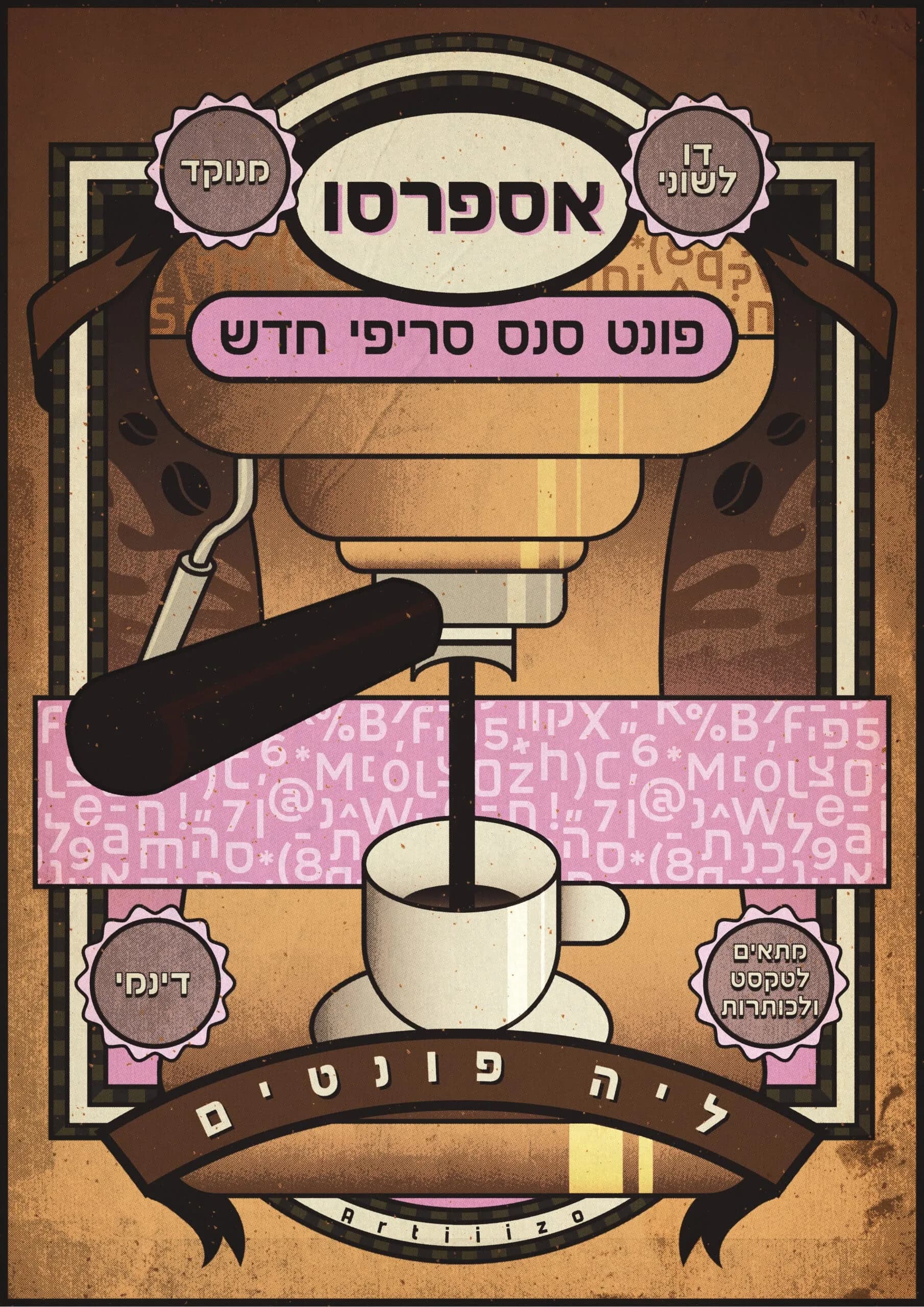
אספרסו אספרסו הוא פונט שיעיר את העיצובים שלכם! - הבחירה המושלמת למי שרוצה להוסיף קצת ארומה לטקסט!מה מיוחד בפונט אספרסו?עיצוב מודרני עם נגיעות קלאסיותקריא מאוד גם בגדלים קטניםמגיע ב-6 משקלים שונים, מדקיק ועד כבדתומך בעברית ואנגלית דקיק קל רגיל בינוני בולד כבד נסו אותי | רישיון בחירת אפשרותדסקטופווב משקל בחירת אפשרותדקיקקלרגילבינוניבולדכבדמשפחהנקה כמות של פונט אספרסו הוספה לסל עיצוב פוסטר: studio artiiizo